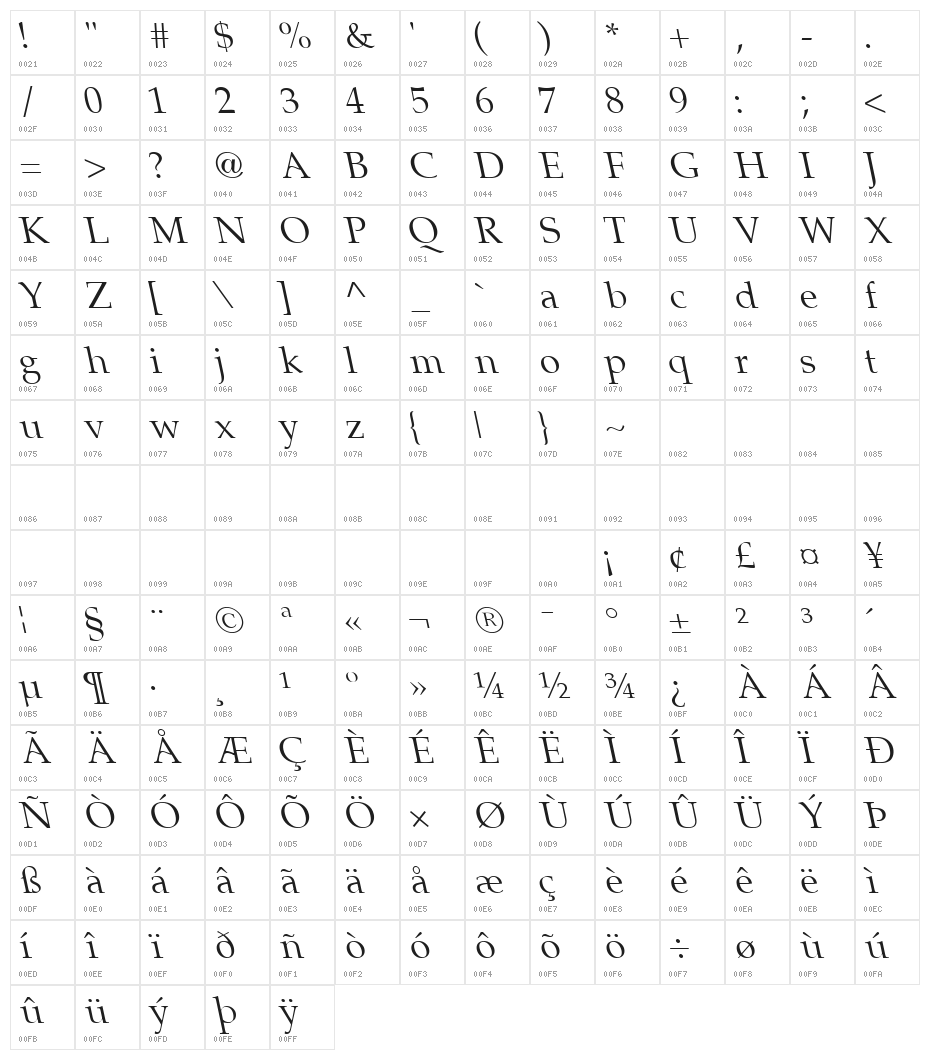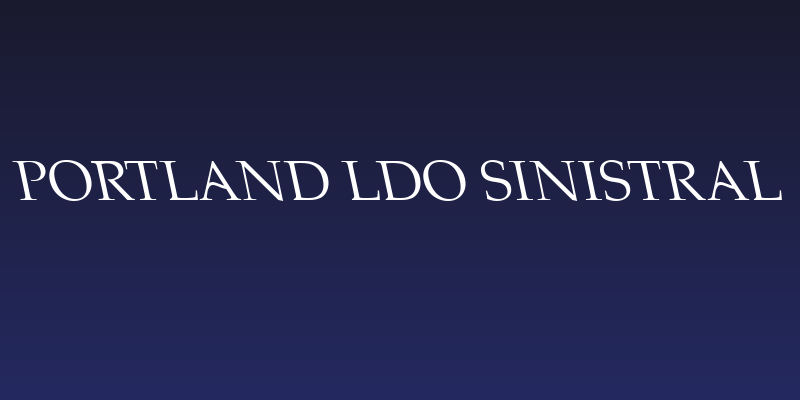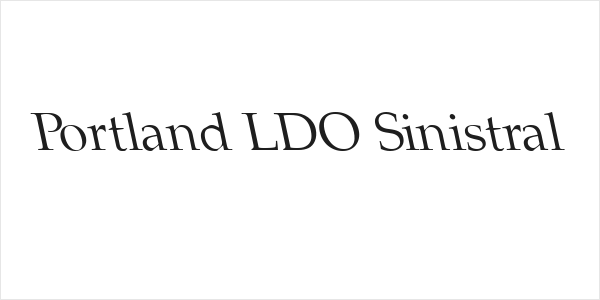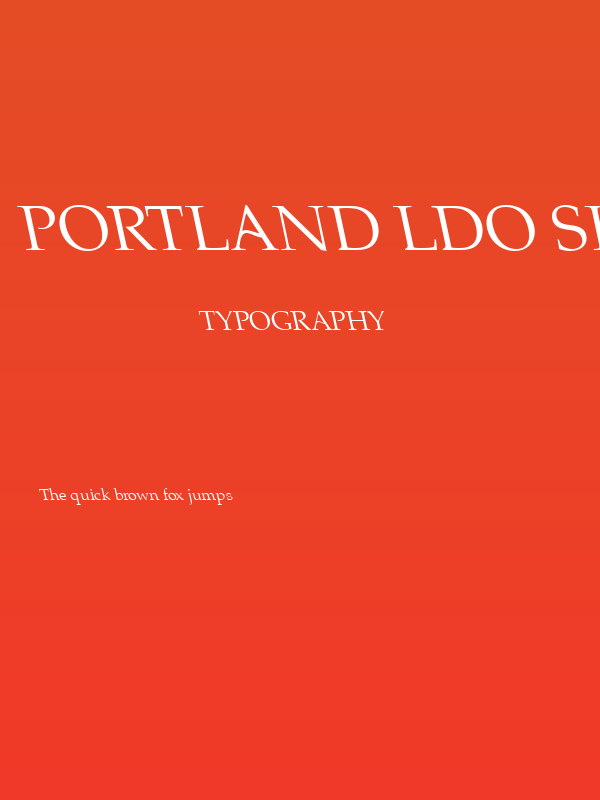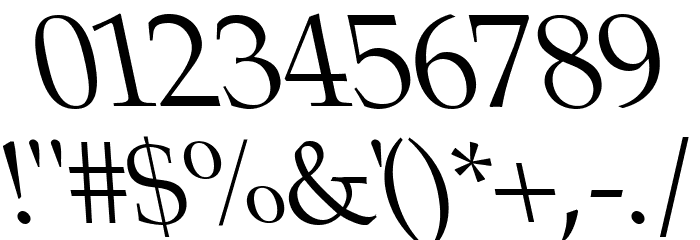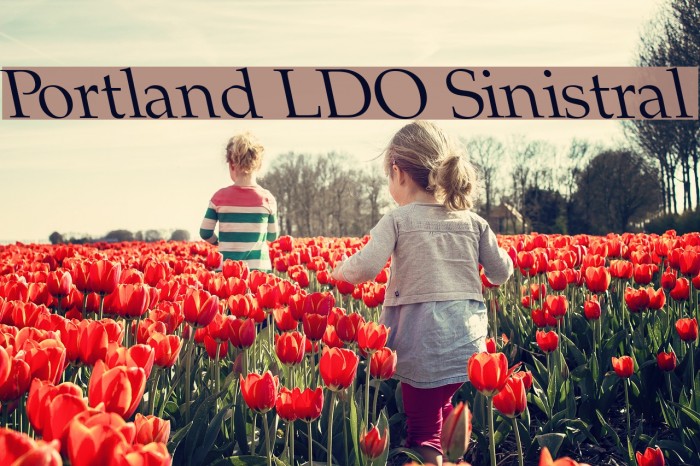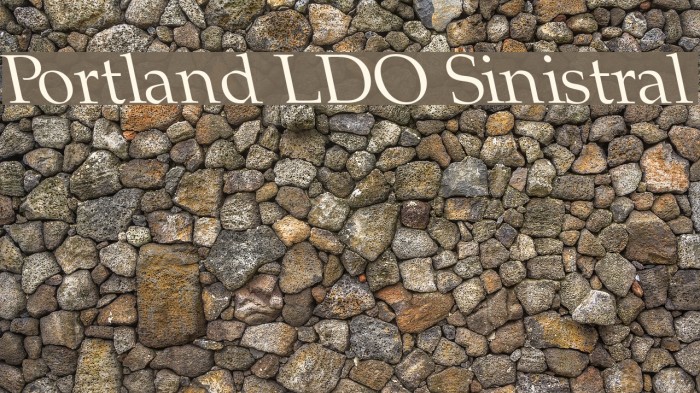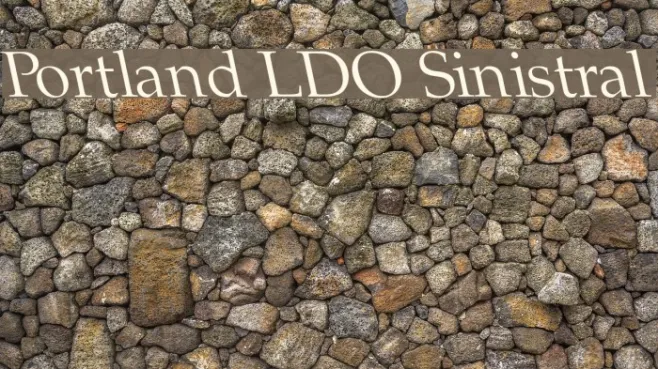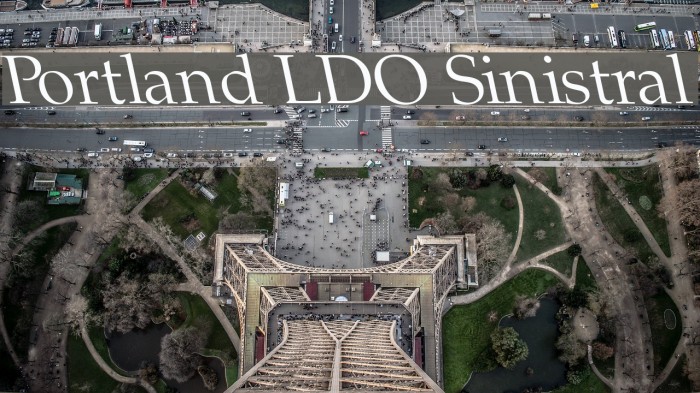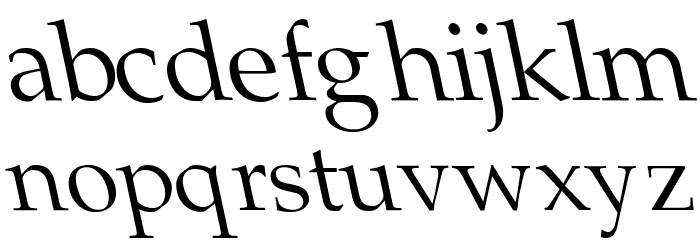
Portland LDO Sinistral Font
| Categorías | Serif |
| Estilo general | Classic |
| Caso de uso | Headlines, Body text, Logos |
| Proyectos propuestos | Ideal for editorial design, book covers, formal invitations, and branding projects that require a touch of sophistication. |